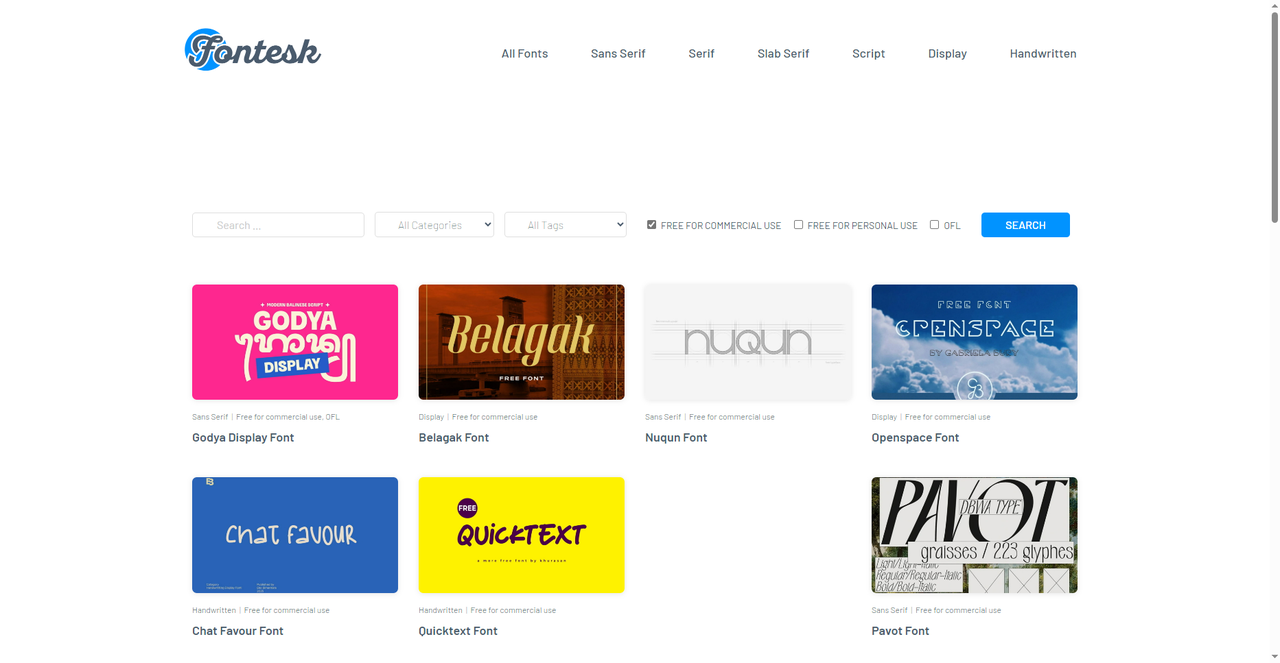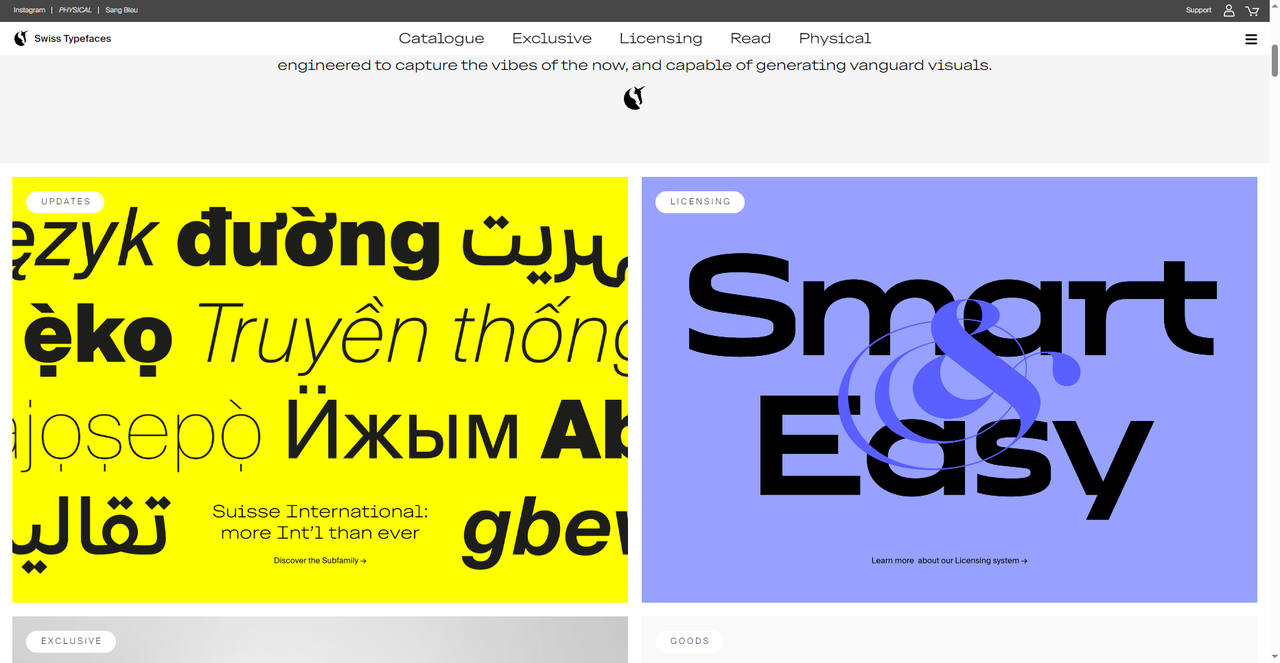
创意字体合集!6个宝藏字体下载网站
相信各位设计师在设计海报的时候都遇到过尝试了好几种字体但是都没有自己你想要的感觉,总觉得差点意思。一旦找到了对的字体,整个海报都变得焕然一新。其实这就是创意字体的魅力,字体有时候不仅仅是在传递信息,同样也是在传递一种美感、一种情绪,也是艺术表达方式的一种。好的字体值得学习和参考。那么今天我就为各位设计师准备了 6 个宝藏级别的创意字体下载网站,从国产神器字由到国际顶尖工坊,希望能帮你更快地找到那个合适的创意字体。
第一个我要推荐的创意字体合集网站,字由。虽然网站主打的是免费商用字体和丰富的字体资源库,但是依旧有不少高质量、可以供免费下载的创意字体。如果你想要寻找创意字体相关的灵感,可以来字由找一找,相信你一定能够有所收获。推荐字由最主要的原因还是因为其户端内置了5000多款精选字体,总有一款是你想要找到的,除了经典字体,也有大量风格独特的创意字体——手写体的随性、书法体的力道、艺术字体的巧思,你都能在这里翻到。每一款字体都标注了授权类型,不用担心误用侵权。而且相比起其他网站还要下载以后还要重启软件来安装文字,字由支持在 Photoshop、AI、Sketch、Figma 等设计软件里一键切换字体,不需要下载安装,选中文字点一下就能实时更换。这样当你试用字体的时候就不用再来回切换器软件了。而且字由内置的AI识字、AI擦除、AI配字等功能,能解决很多日常杂活。比如看到一张海报上的字很喜欢,拍下来用AI识字识别;做海报时不知道用什么字体,让AI配字根据图片内容推荐。
2、Fontesk
Fontesk 是一个专门收集免费字体的平台,它的免费商用字体版块非常庞大——目前收录了超过 6500款 免费可商用字体。其中就包括不少创意字体,你可以在相关的创意字体合集中找到,这得益于网站的分类做得极其细致。你可以按风格(Sans Serif、Serif、Script、Display等)、按标签(复古、手写、科技感、Y2K等)、按授权类型来筛选。每一款字体都有详细的预览图和下载链接。Fontesk 的标签系统很有意思,除了常规的风格分类,还有很多“情绪标签”——比如“Edgy”(前卫)、“Bouncy”(活泼)、“Romantic”(浪漫)、“Cyberpunk”(赛博朋克)。如果你在做一个有特定调性的项目,但不知道用什么字体,可以试试点进这些标签,说不定能有意外收获。
3、Swiss Typefaces
这一款推荐的和以往做的推荐都有比较大的区别,因为这一期我们主打服务的是需要创意字体合集的设计师们,我不得不拿出 Swiss Typefaces 这一家总部位于瑞士苏黎世的高端字体设计公司。他们的字体以极致的工艺和纯粹的设计著称,在全球专业设计圈享有极高声誉。比如经典的 Akkurat、GT America、Circular 等,都是设计师眼中的“神作”。需要注意的是,Swiss Typefaces 的字体全部需要付费购买,并且价格不菲。完全无须担心货不对板或者是质量问题,自己一看便知。就算不购买,来这里找一下自己喜欢的字体,然后再去其他网站寻找平替的创意字体也是完全可以的。
4、 FontBrief
FontBrief 是一个很特别的字体推荐工具——它是一个根据“性格”帮你筛选字体的工具。这样就方便我们寻找自己想要的创意字体,并根据其提供的字体网站进行下载。进入网站后你可以通过一系列滑块来定义你想要的创意字体,比如说有表现力的字体、优雅的线体字体、严肃规整的字体,又或者是有创意的、前卫的字体,等等,一应俱全。调整完这些参数,系统会从数据库中筛选出符合这些“性格特征”的字体,生成一份精选列表。每一款字体都标注了设计师和授权方式,点击可以跳转到下载页面。
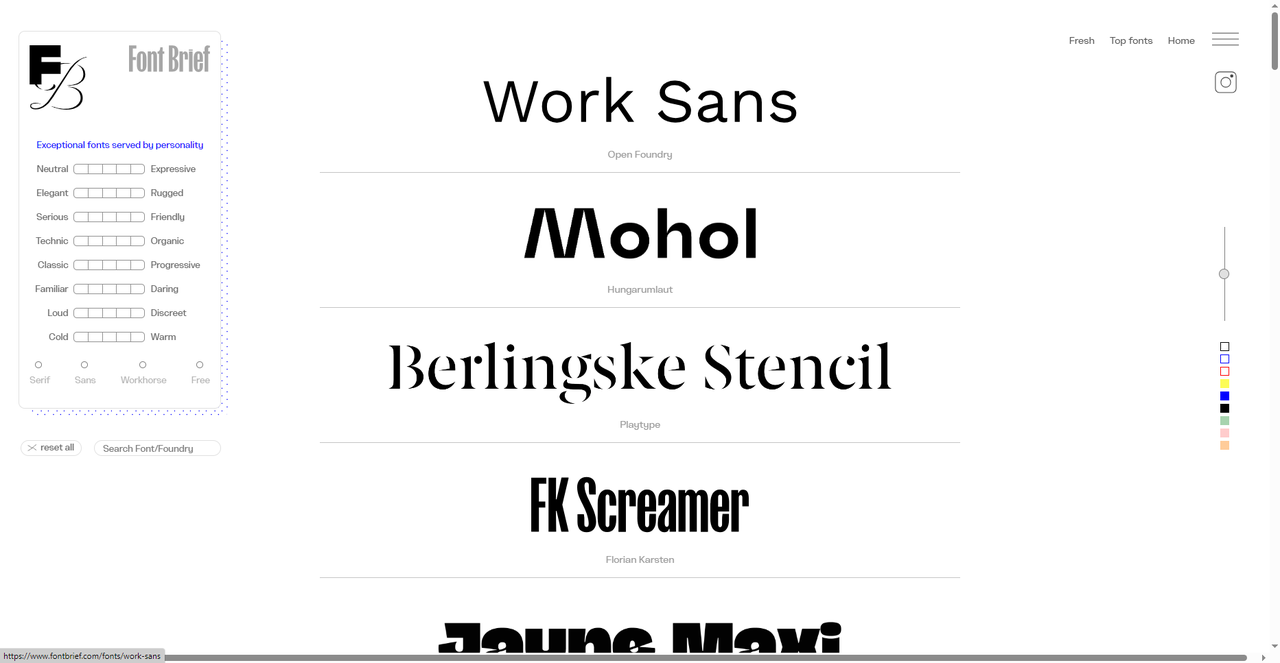
5、Hoefler&Co.
Hoefler&Co. 是国际顶尖的字体设计公司,这一宝藏字体下载网站的设计非常优雅考究,比如经典的 Gotham、Whitney、Chronicle 等都是获得业内一致好评的。而且网站首页也会推送一些精品文章,比如说“Italics Examined”(斜体字探析)——他们不止卖字体,更注重字体文化和学术研究。和 Swiss Typefaces 一样,Hoefler&Co. 的字体全部需要付费授权,价格不低。这对于创意字体有高要求的设计师十分友好,也同样可以作为设计灵感来源。
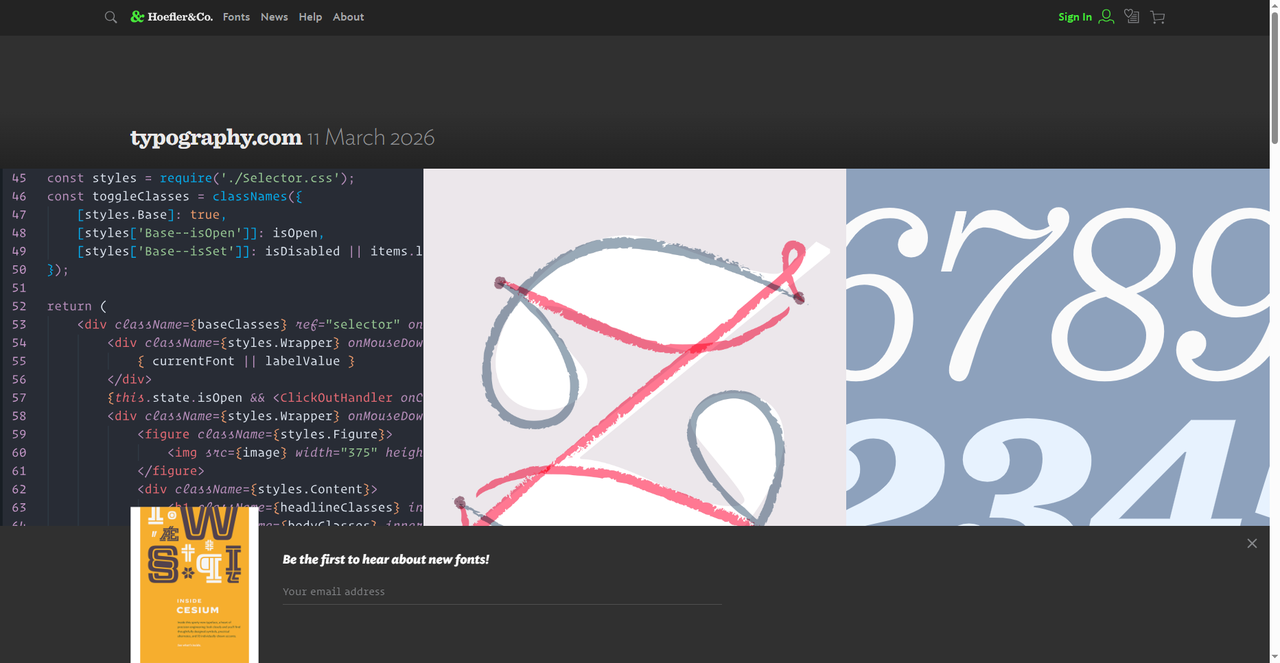
6、Squarespace
虽然乍一看这个网站像是个人作品集展示网站,但是其内置了一批高质量、可商用的西文字体,支持直接在网页上试用,Squarespace 合作的字体工作室包括 Commercial Type、Type Network 等,平台上线的字体都经过精心挑选,死神当之无愧的创意字体合集宝藏网站,一些免费商用的字样不仅可以帮助你设计作品,还能够用来帮助你搭建网站。需要提醒的是,在这个网站里你不能直接下载字体文件,但是你可以通过浏览器开发者工具可以看到字体的名字和应用效果,再来决定是否购买。